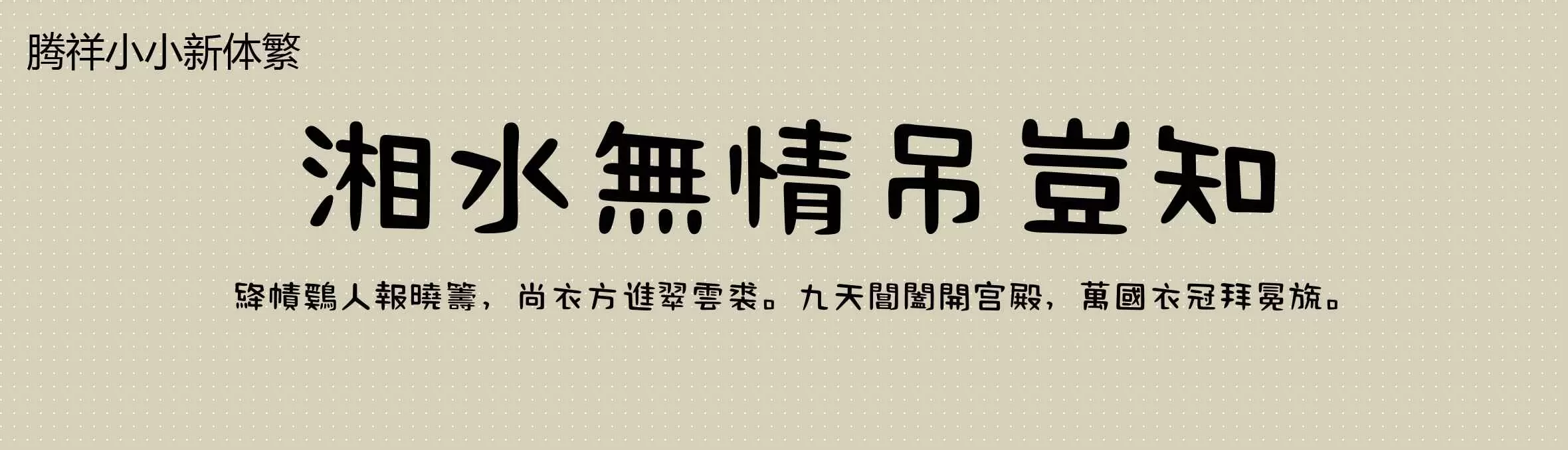
腾祥小小新体字体由设计师孔淼先生手绘设计字体初稿,再由腾祥公司二次设计制作成的美术体字库。风格鲜明、特点突出。笔画圆润灵活、结构不拘一格。起笔重落笔轻,横笔画好似“蜡笔小新”粗粗憨憨的两道眉毛,故取名为“小新体”。小新体的笔画不拘泥、不造作、不刻意、笔画间透出质朴、天真、可爱、呆萌的童趣性格。看似无拘无束少儿字体,实则流露作者书写之功与童趣之心。本款字在不影响阅读的前提下尽显其特性。本作品可适用于印刷出版儿童读物、包装设计、广告设计、网页设计等。